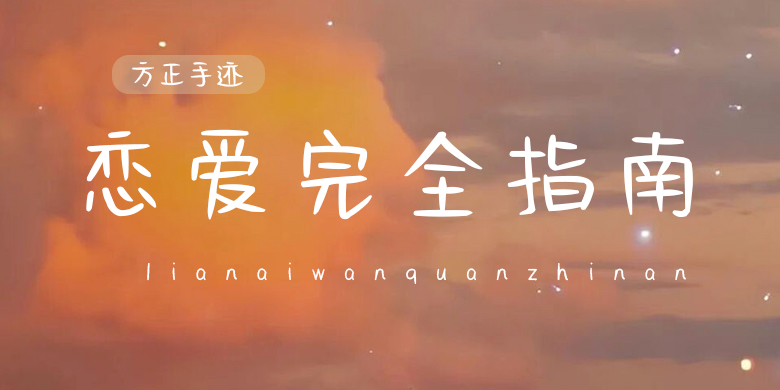
方正手迹-恋爱完全指南
字体品牌: 方正手迹 设计师:宋昱东 字体分类:创意书写 字体属性:精品字 字符集:简繁扩展(GBK) 发布时间: 2020
恋爱完全指南这款字体笔画圆润饱满,既有传统书法文化中的中庸、圆融,又具备现代字体的美观实用,整体简洁明了而又形象生动。适用于广告设计、名片设计、包装印刷、产品设计等领域。